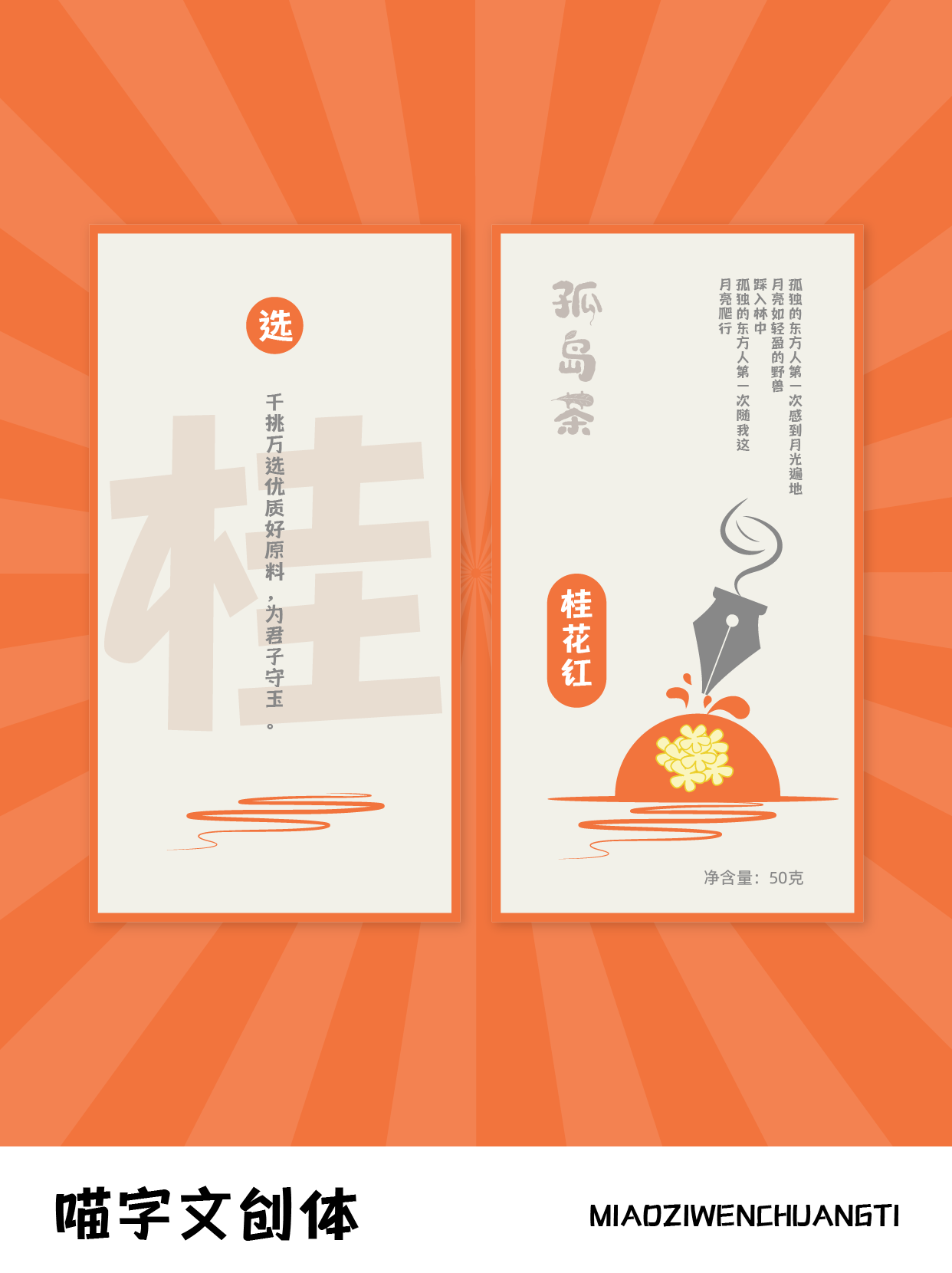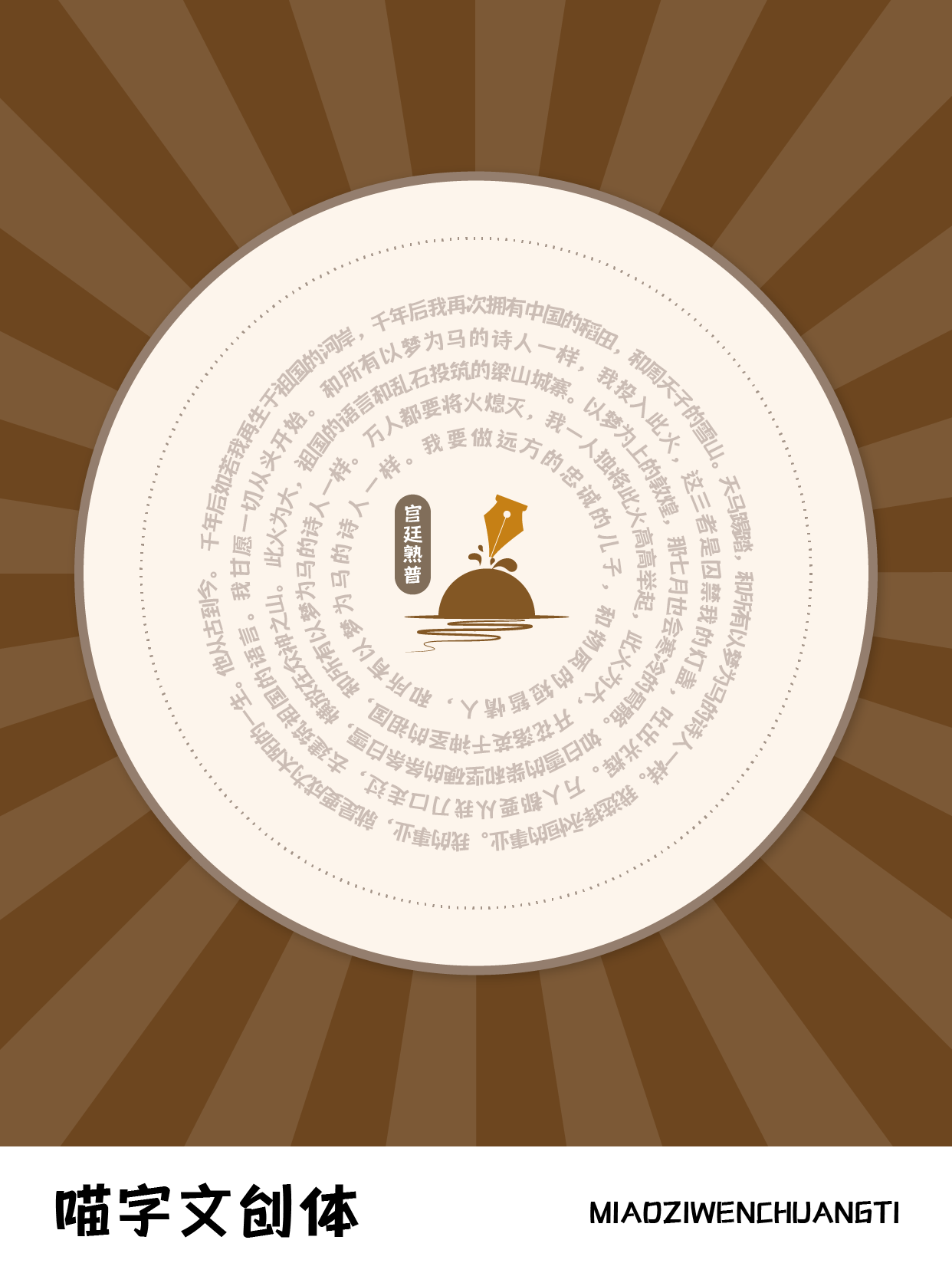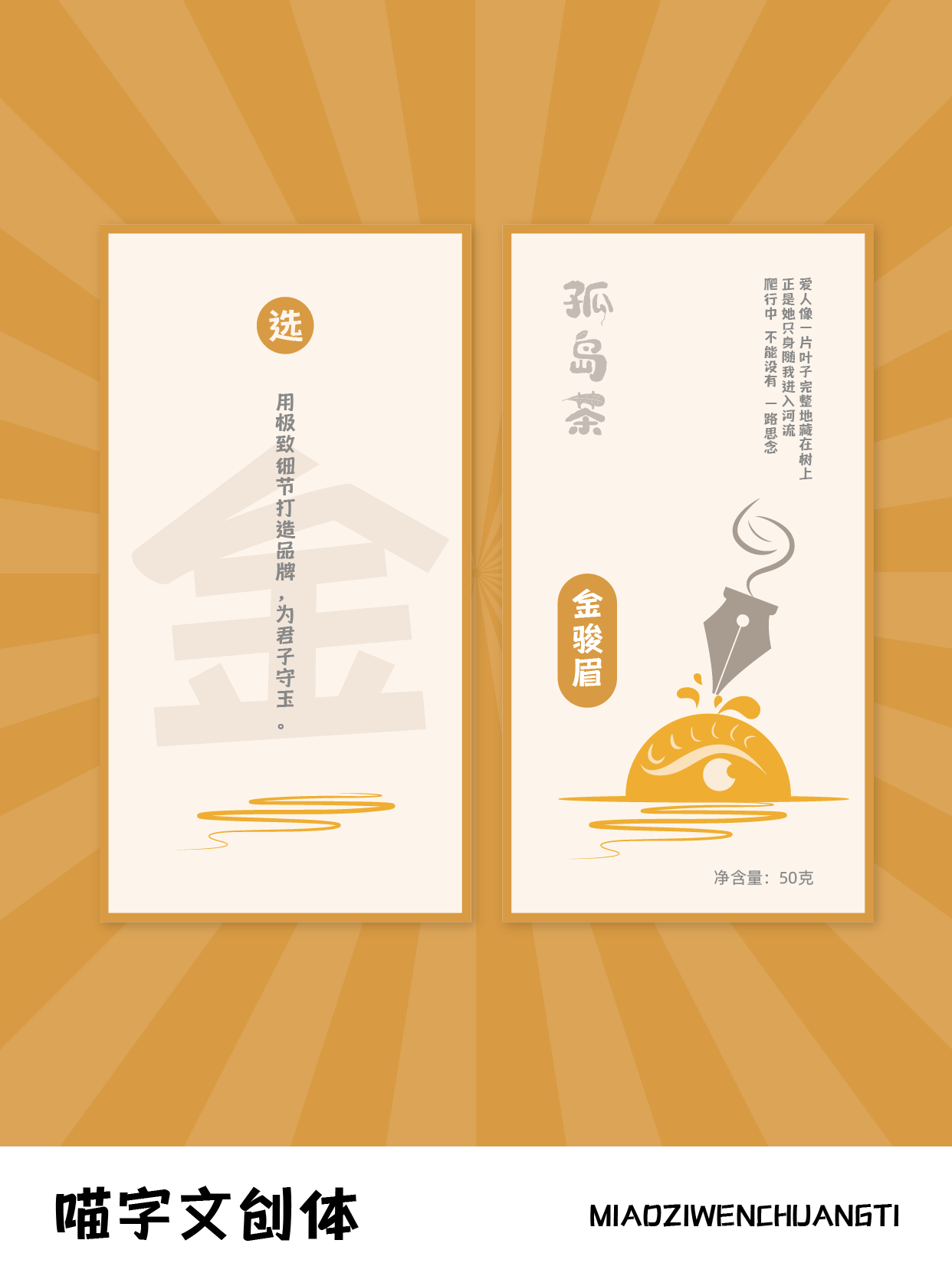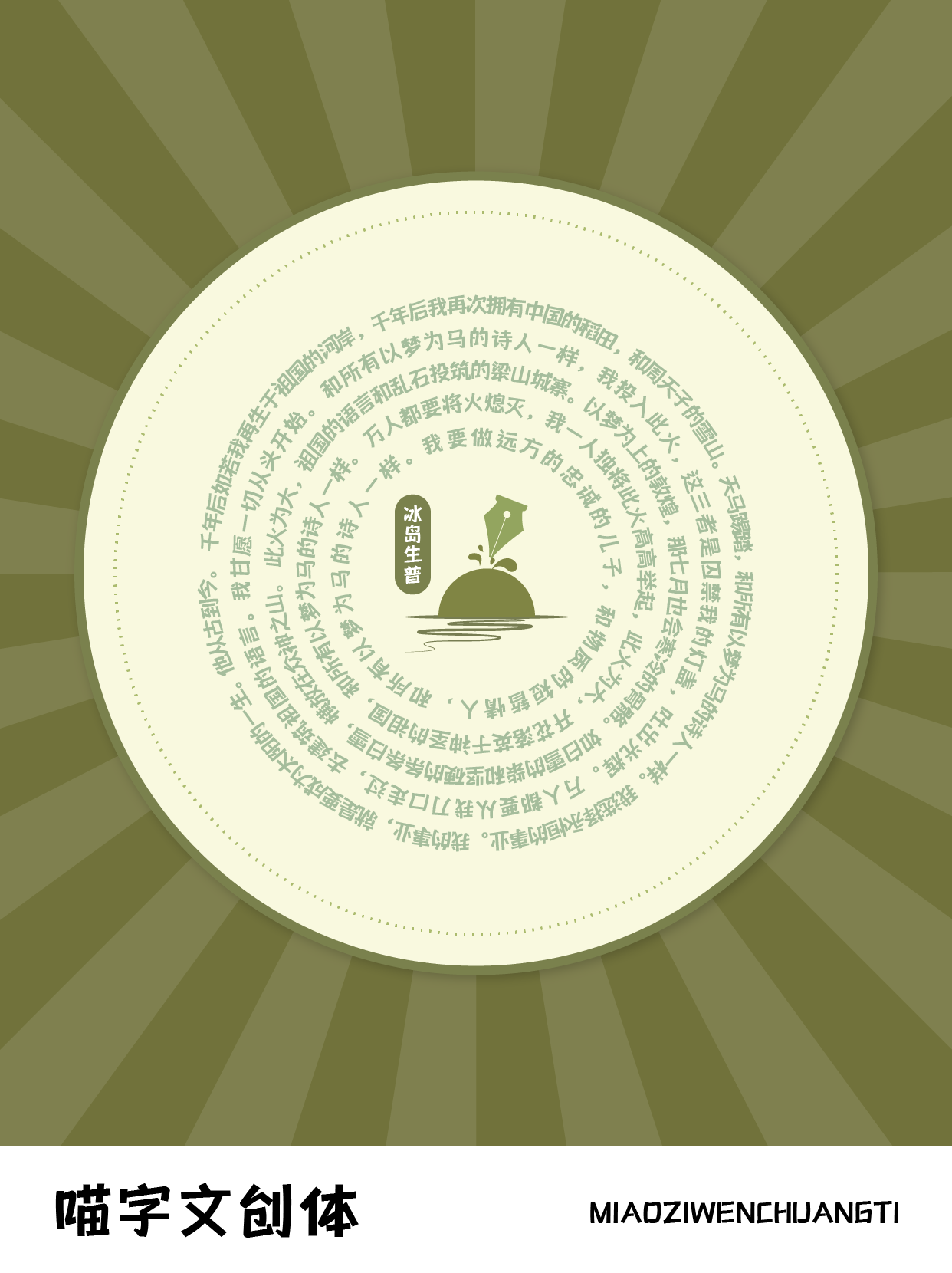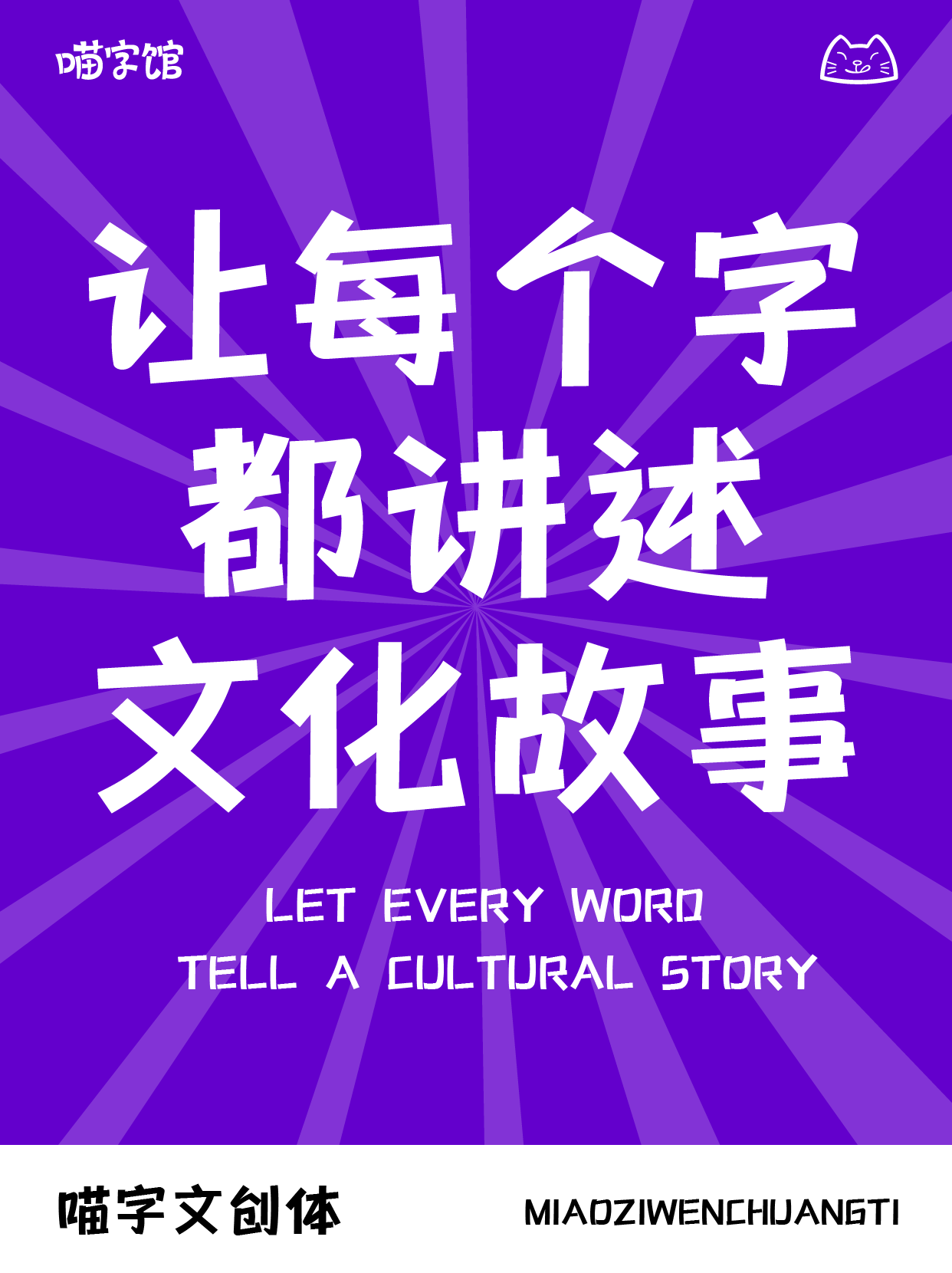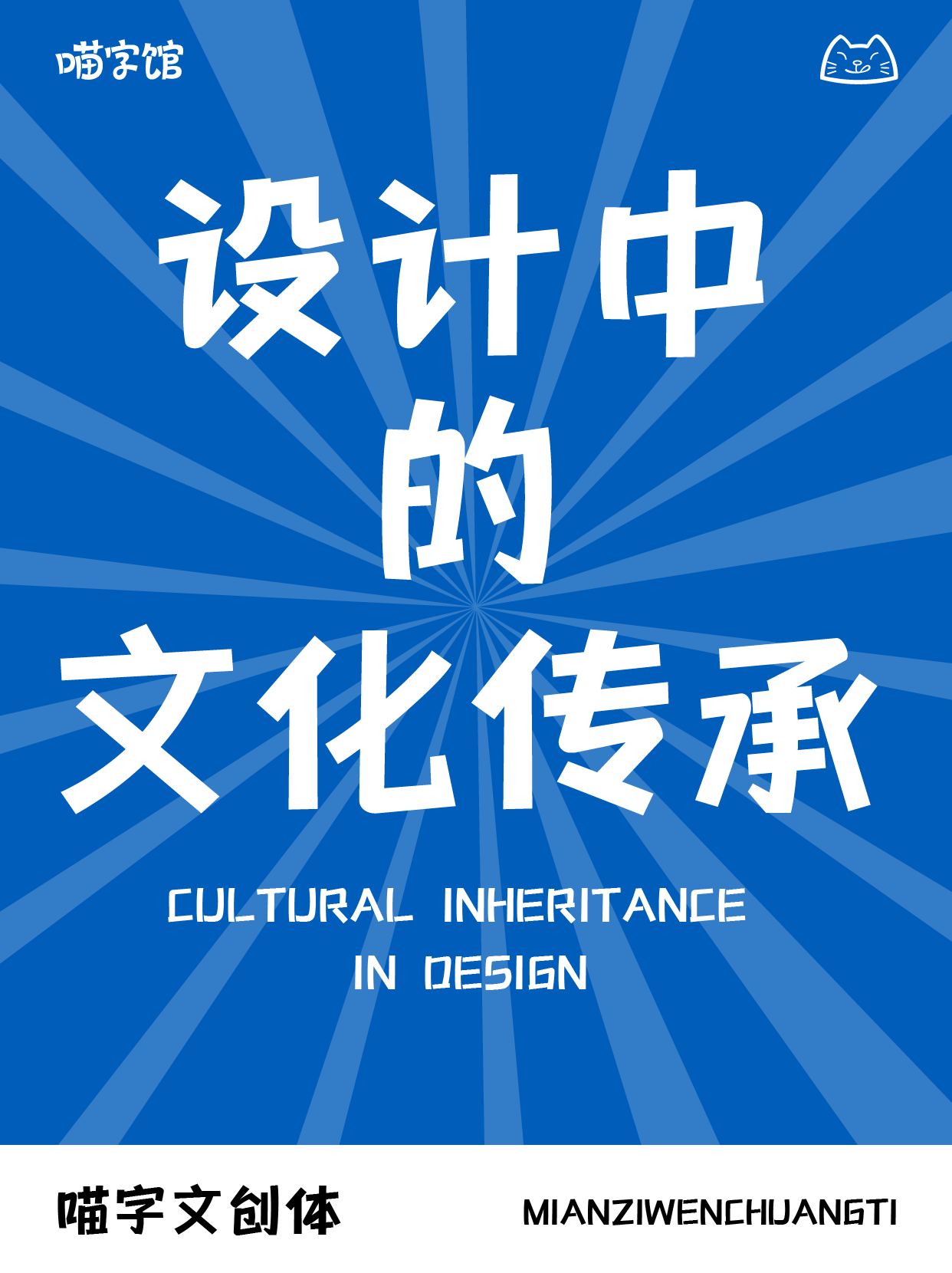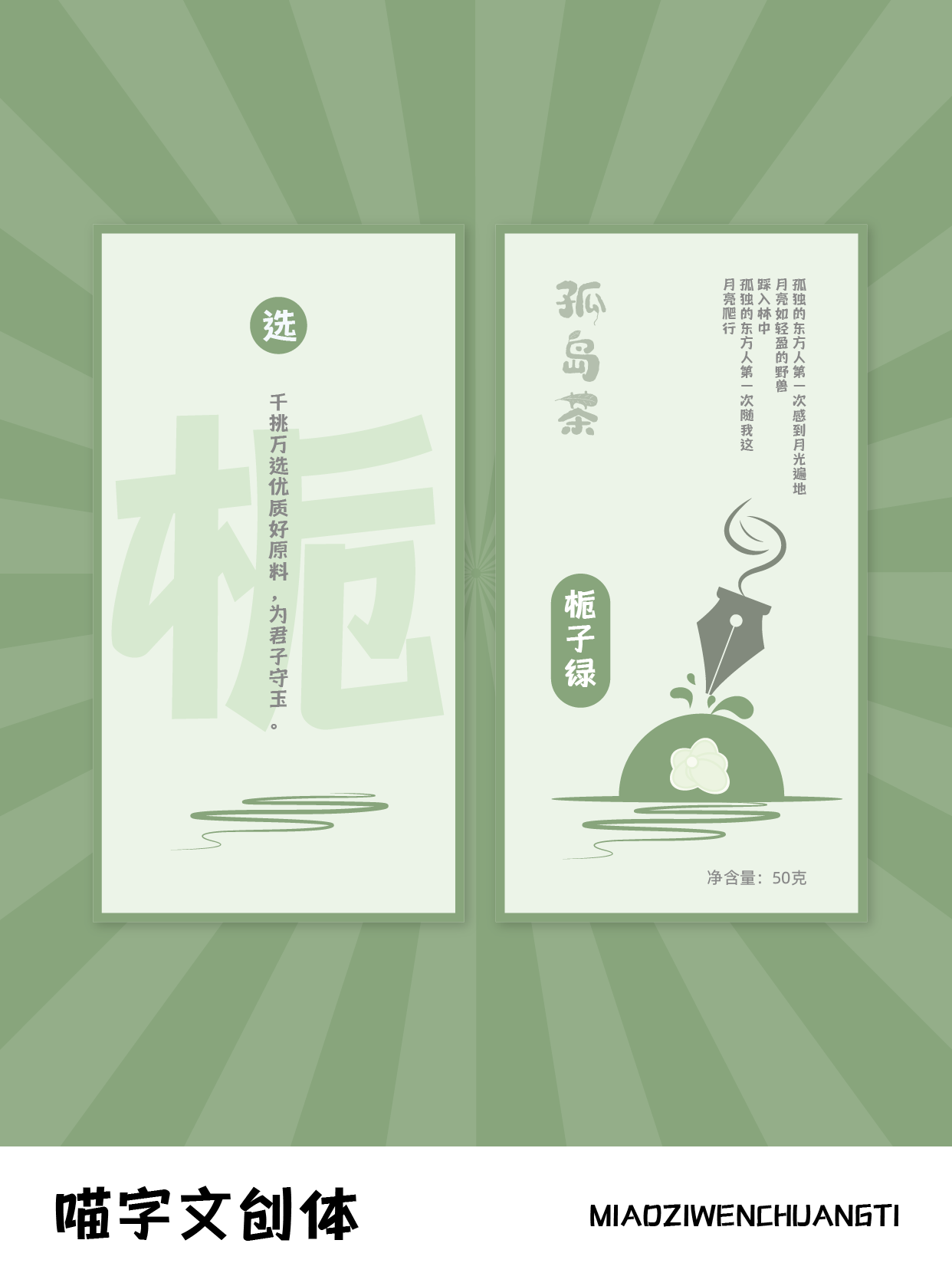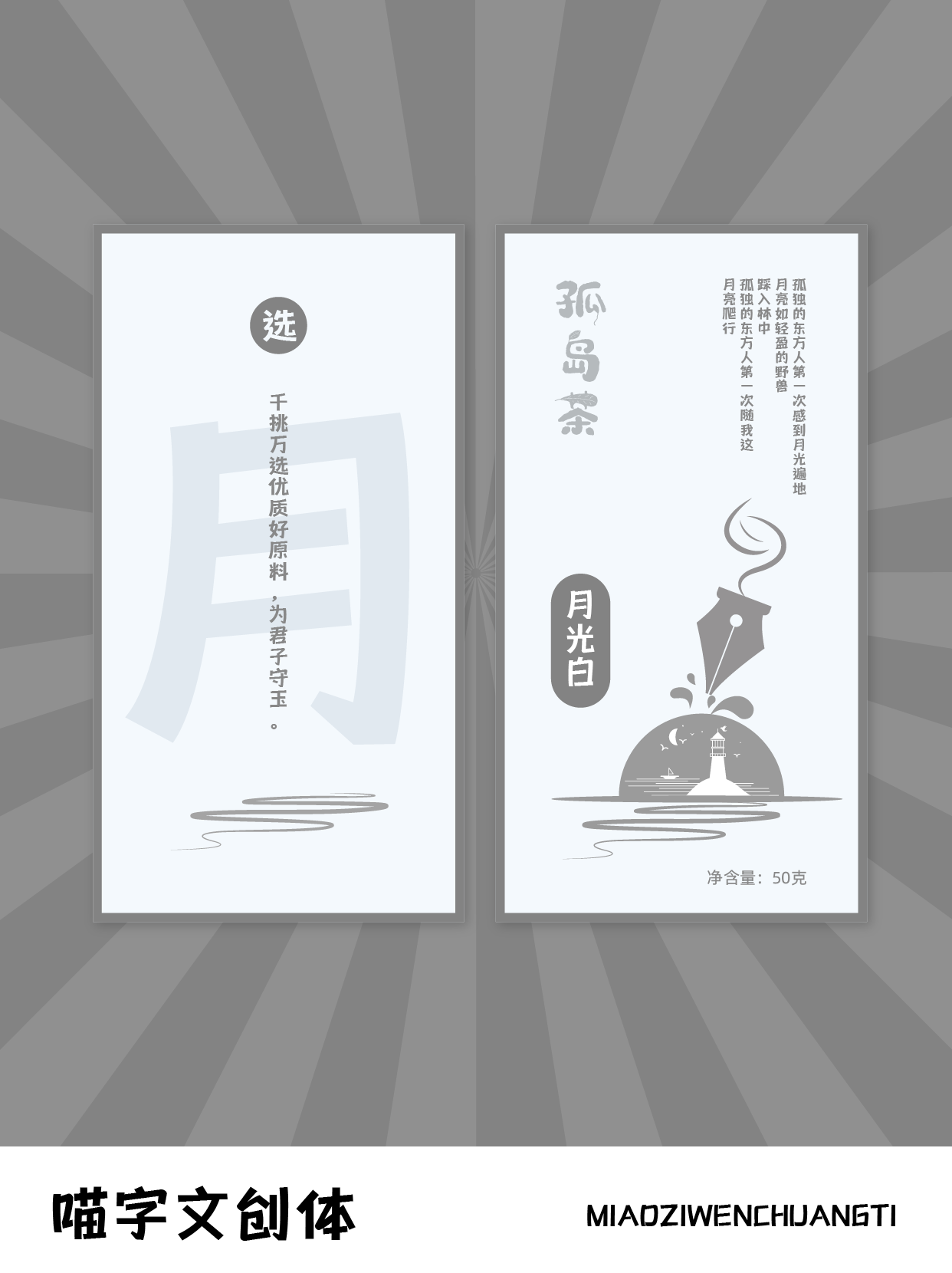
喵字文创体
MiaoZiWenChuangTi
喵字文创体一款专为文化创意产业精心打造的定制级字体产品,以其独特而富有创意的设计理念,在传承与创新之间找到了精妙的平衡点。这款字体深度挖掘并巧妙融合了传统行书艺术中的结构穿插精髓,行云流水般的笔画走势,既保留了书法艺术的灵动韵味与深厚底蕴,又在现代设计美学的框架下实现了新的解读和升华。